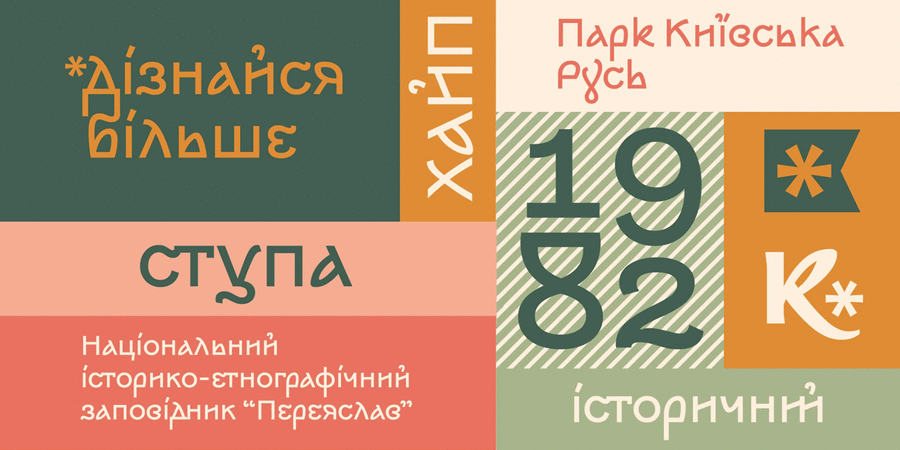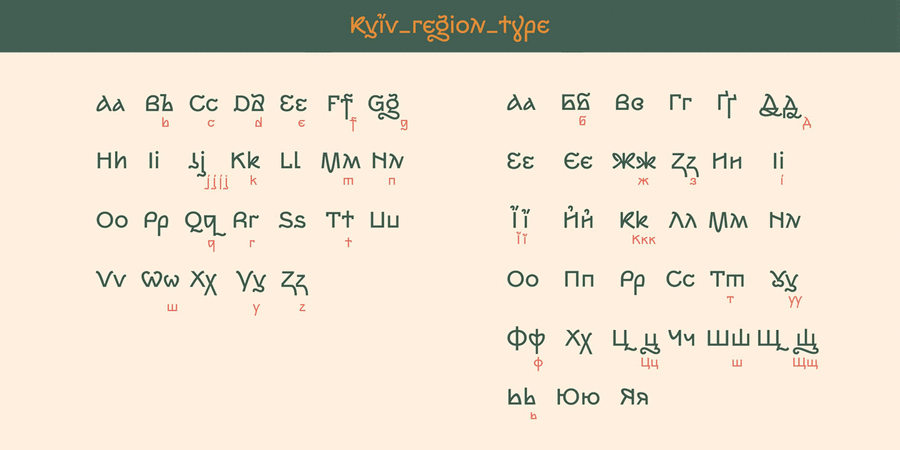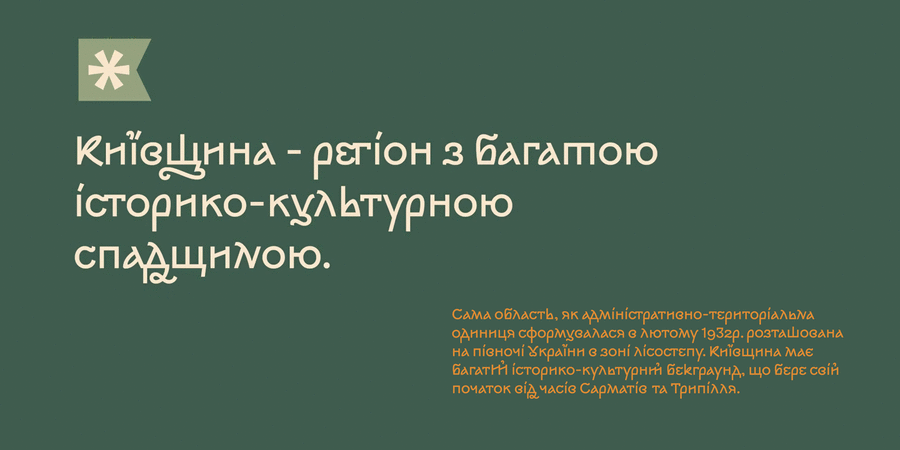
Опис шрифта Kyiv Region TypeОригінальний безкоштовний шрифт створений спеціально для територіального брендингу Київської Області. Стиль Київщини розроблено студією White Studio Design. Шрифт Kyiv Region Type поєднує давню історію з авангардистськими експериментами. Форми півуставу та скоропису, характерні для часів Київської Русі та Українського Бароко, поєднуються з конструктивізмом двадцятого століття, який, через сто років, знову у тренді. Вийшов сучасний геометричний гротеск з розчерками, альтернативами, лігатурами та історичними формами, яким можна оформлювати тематичні покажчики, рекламу, упаковку, сувеніри та навіть історичні тексти церковно-слов'янською мовою. Kyiv Region Type розповсюджується за умовами безкоштовної ліцензії SIL Open Font License (OFL). Шрифт розробив Дмитро Растворцев у 2021 році.
Асоціації з сімейством шрифтів Kyiv Region TypeОсобистість і характер гарнітури:
історичний, гнучкий, лихий, рухливий, розв'язний, динамічний, вільний, самобутній, етнічний, природний, натуральний, традиційний, героїчний, старовинний, козацький, вольний, колоритний, живий, темпераментний, мотивуючий, активний, органічний, племінний, моторний, розмашистий, прямокутний, амбітний, незграбний, ламаний, рубаний, ігровий, квадратний, експериментальний, характерний, незвичайний, стійкий, якісний, сучасний, модний, оригінальний, міцний, помітний, сміливий, твердий, впевнений, жорсткий, грубий, різкий, чіткий, свіжий, ефектний, культурний, цікавий, дивний, релігійний, церковний, православний, крафтовий, артізанальний, біблійний, християнський, сакральний, різдвяний, дерев'яний